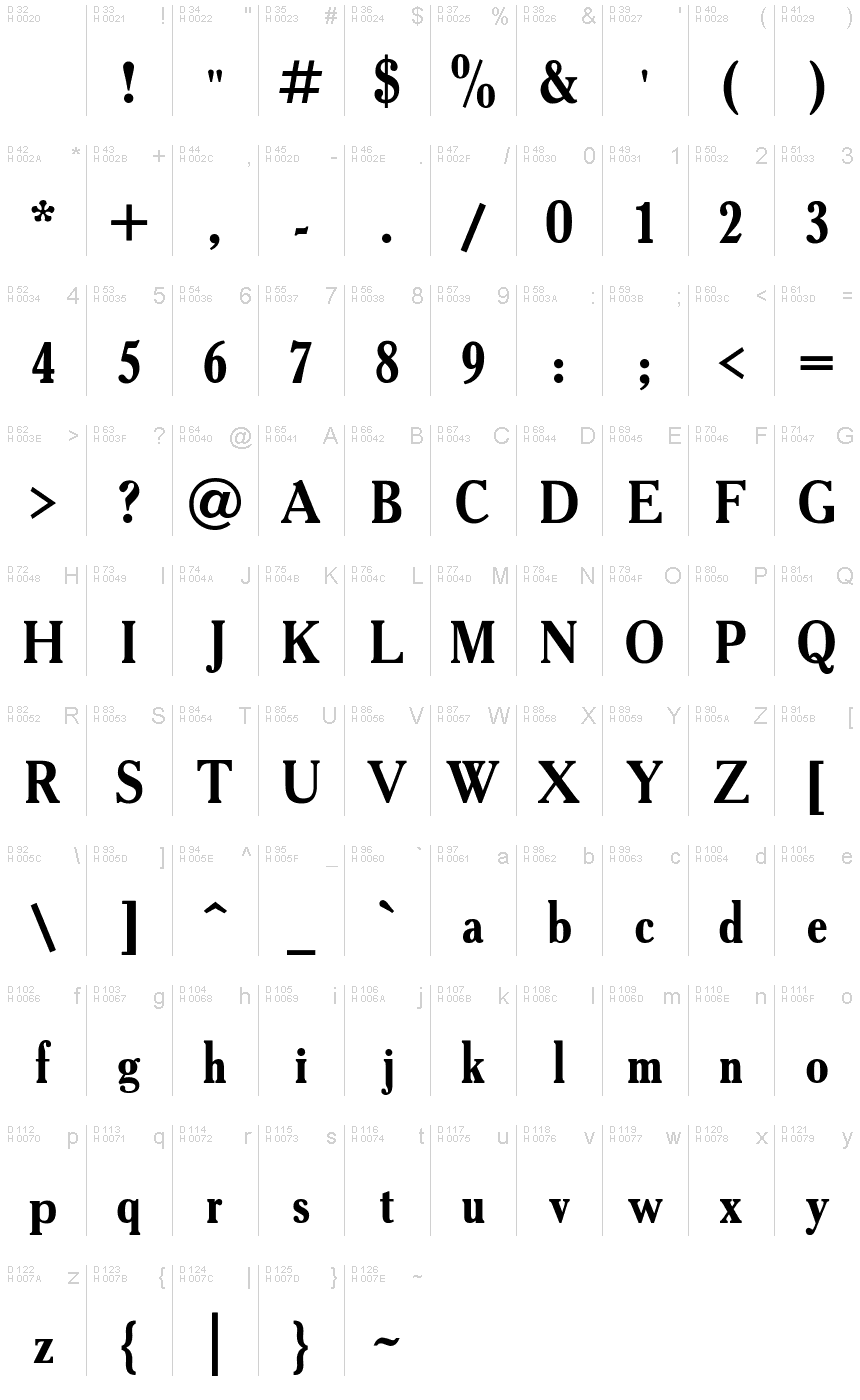
Akademische schmalfette
Die Verfasserversion der berühmten «Akademische schmalfette» Berthold-Garnitur 1910, mit Ergänzungen, außer den Buchstaben der traditionellen russischen Orthografie, deutscher Umlaute & des «sz» («ß»), die für ine vollwertige Förderung der deutschen Sprache notwendig sind, sowie samt eines Paars Buchstaben mit dem Makron, die für die Wiedergabe von Gräzismen mittels lateinischer Schrift notwendig sind, sowie des neu eingeführten russischen Rubelzeichens «₽».